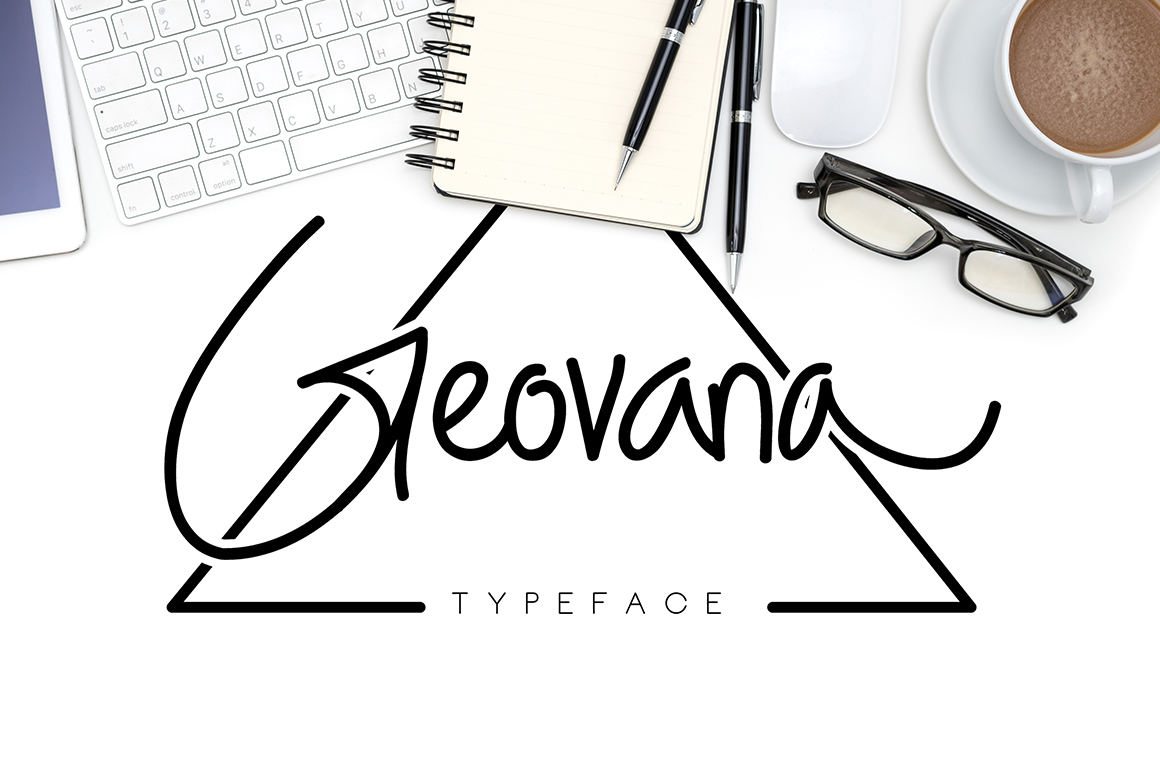
Bem-vindo à Geovana Typeface! Este é um belo tipo de escrita manuscrita perfeito para personalizar suas cartas, anúncios e projetos pessoais. Feito especialmente pelo designer madeDeduk, esta fonte oferece uma autenticidade única que enriquece qualquer projeto em que seja usada. Se você está procurando o download completo desta linda fonte de escrita manuscrita, basta seguir um link que encontrará diretamente no site. Com a Geovana Typeface, sua mensagem ganha vida ao mais puro estilo de escrita criada à mão. Sinta-se à vontade para explorar e descobrir as inúmeras possibilidades que esta fonte pode oferecer para personalizar seus projetos pessoais ou profissionais. Estamos felizes em compartilhar essa fonte com você, aqui na plataforma de downloads, onde cada design é apresentado como um recurso gráfico único. Descubra o poder da Geovana Typeface hoje mesmo!